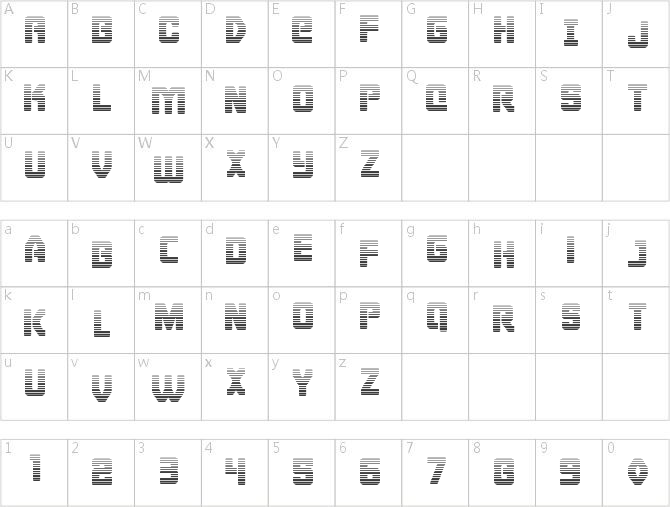
Cyborg Rooster Gradient
Cyborg Rooster Gradient介绍
Cyborg Rooster Gradient字体字库是一款让人赏心悦目、百看不厌的英文字体,适合各类广告和产品包装设计应用,字体大小0.08MB,格式为ttf字体,上传用户是邹湾湾湾湾,作者/版权方为未知